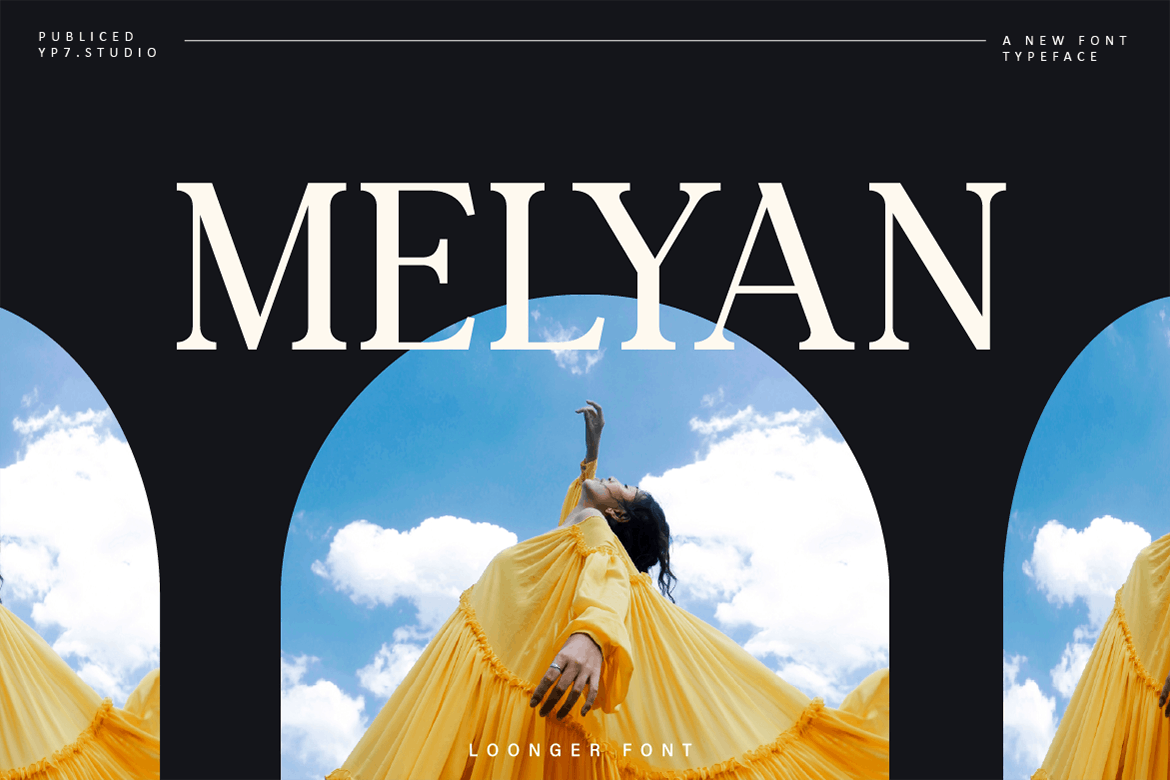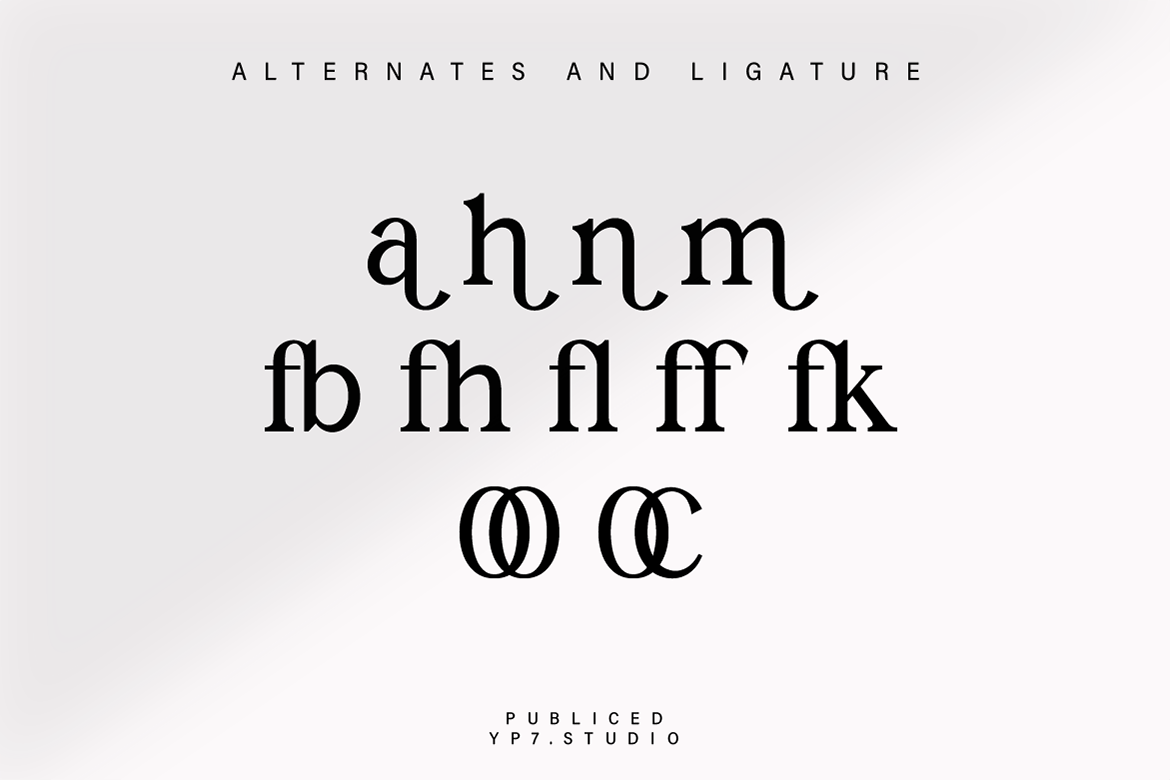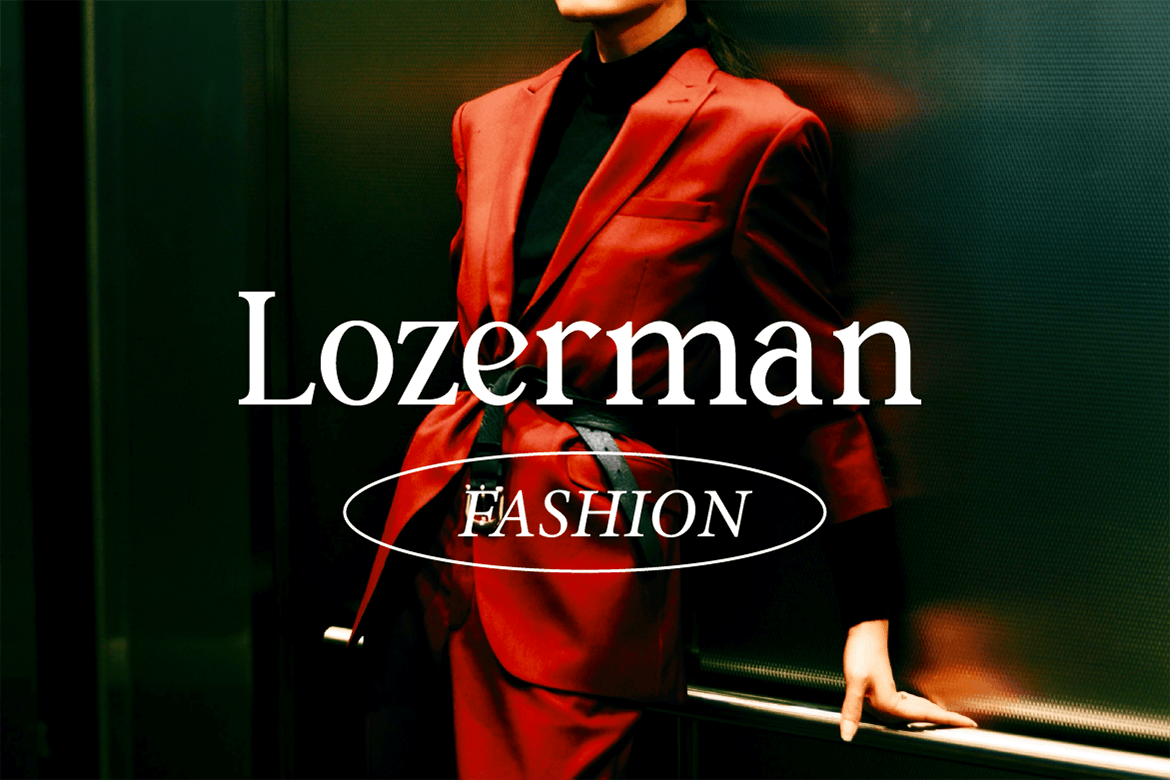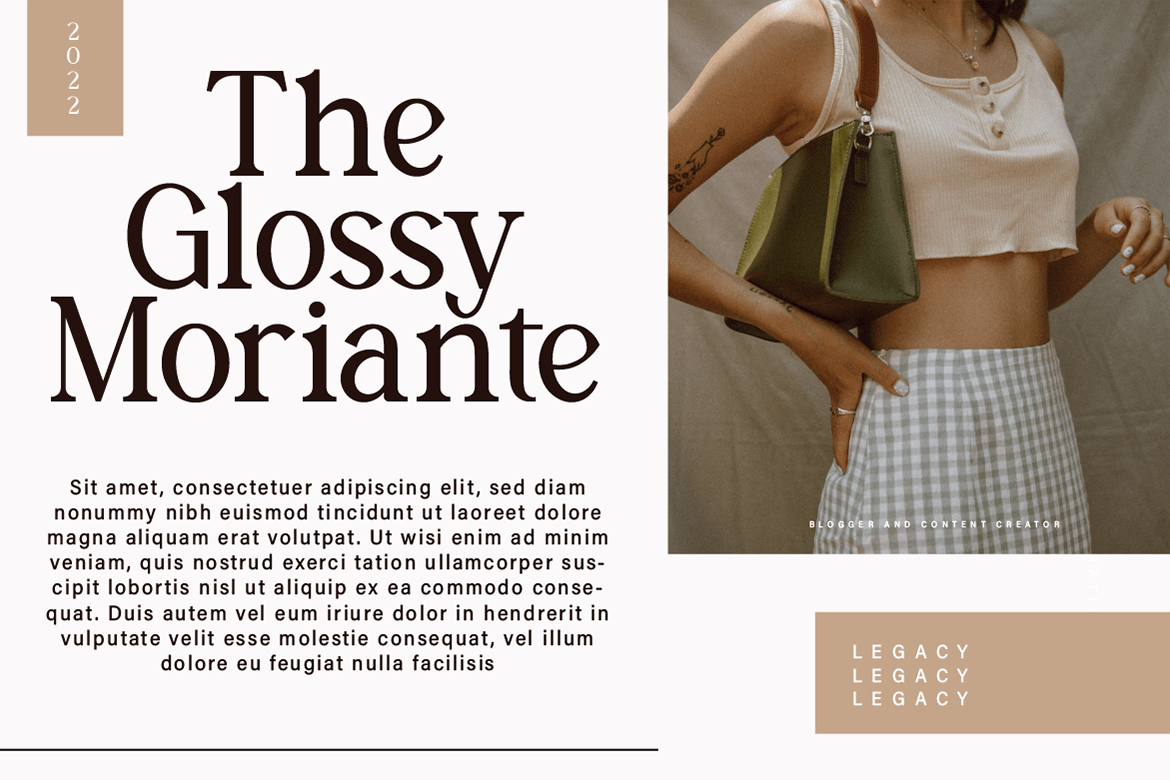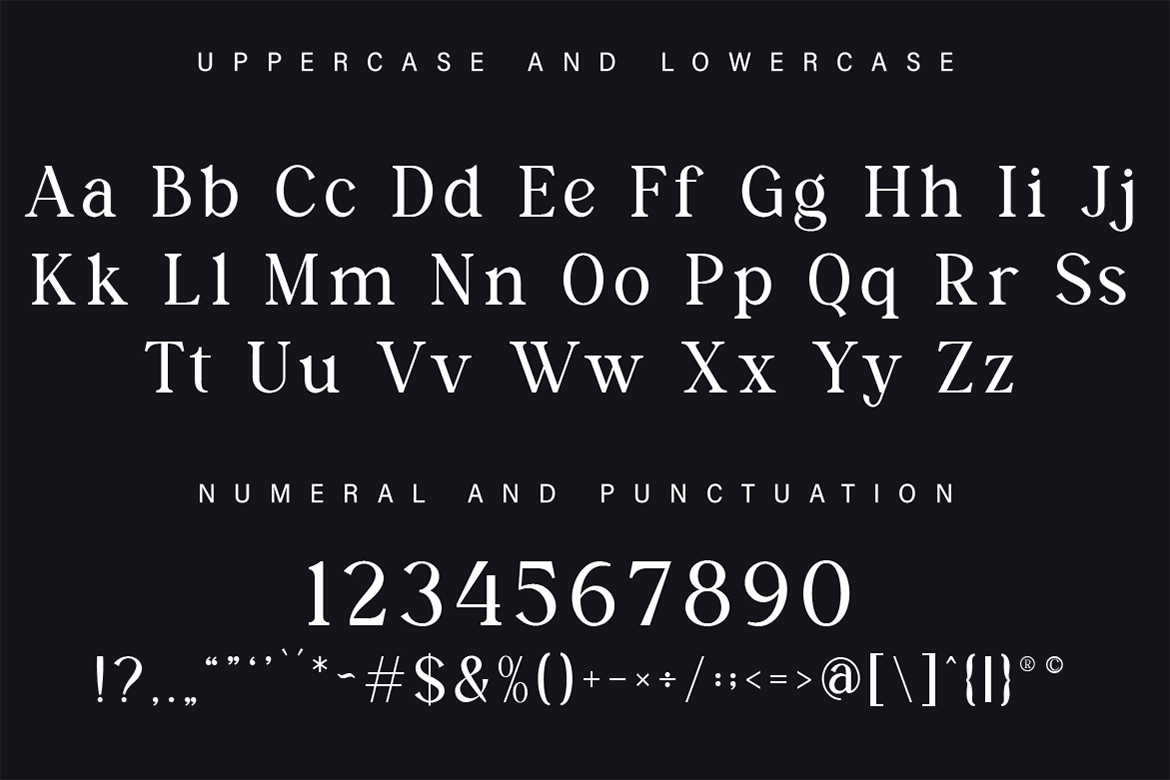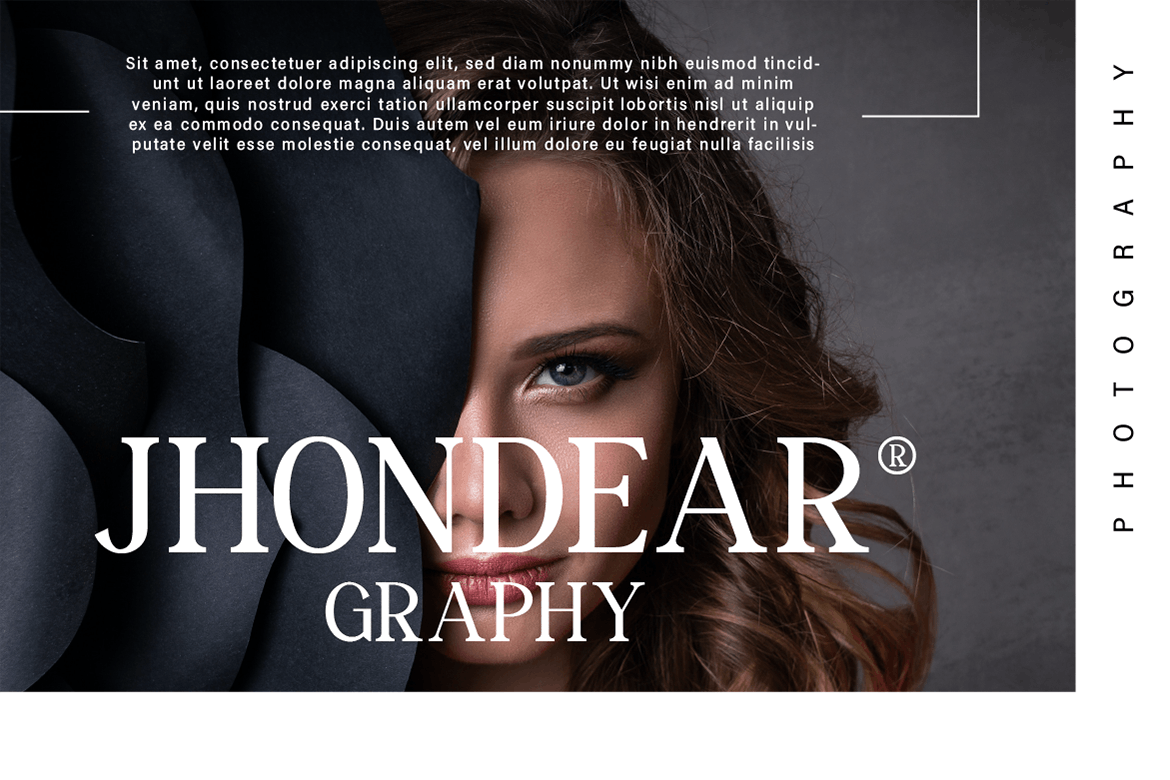
دانلود فونت مدرن سریف - Loonger
Modern Serif Font
فونت سریف مدرن Loonger برای طراحیهای شما مناسب است.
فونت مدرن سریف Loonger
یک انتخاب ایدهآل برای طراحانی است که به دنبال ظاهری شیک و مدرن هستند.
حروف بزرگ
حروف کوچک
اعداد و نشانهگذاری